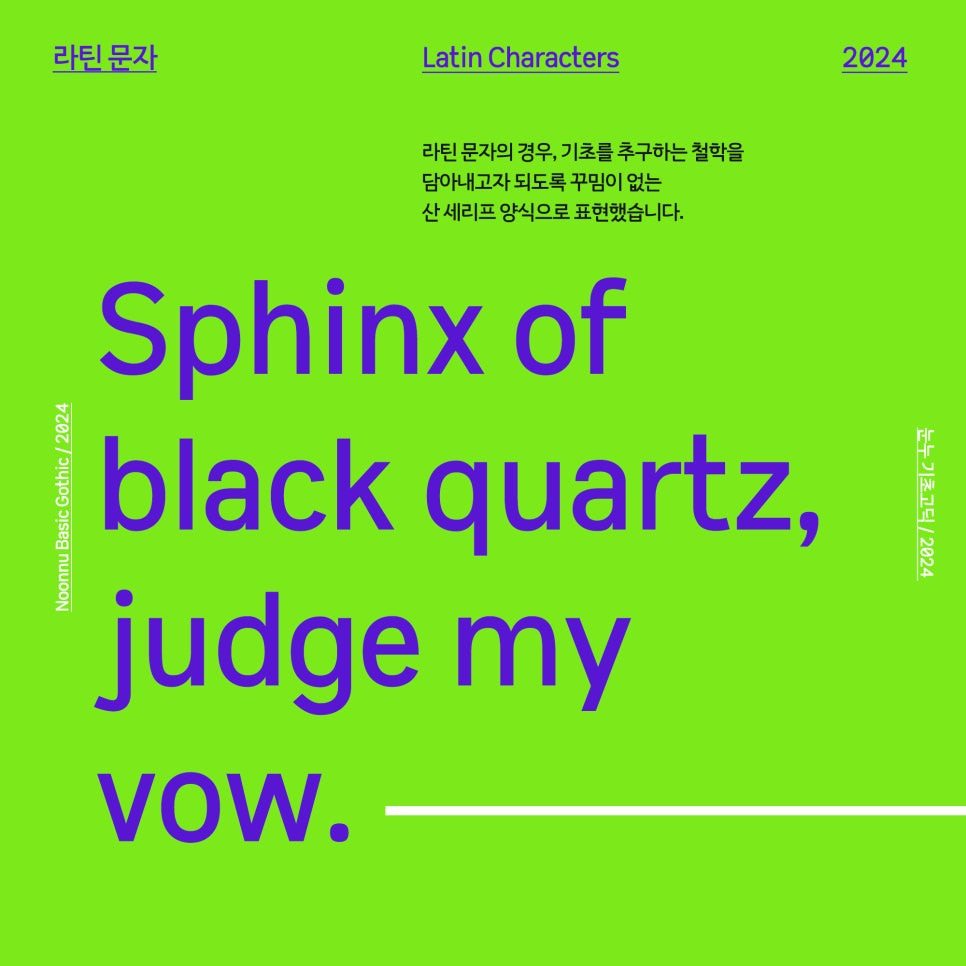
소개
눈누 기초고딕(2024)은 제 578주년 한글날을 기념해 무료 서체 라이브러리 서비스인 프로젝트눈누와 토끼네활자공장 산하 서체연구동의 합작으로 개발된 산 세리프 양식의 무료 한글 서체입니다. 기본을 강조하되 예쁨을 추구하는 토활공과 무료폰트 사이트 눈누가 만나 고딕체를 만들었으며 자칫 운율을 살려 밋밋해보이는 고딕에 활력을 넣었습니다.
서체구성